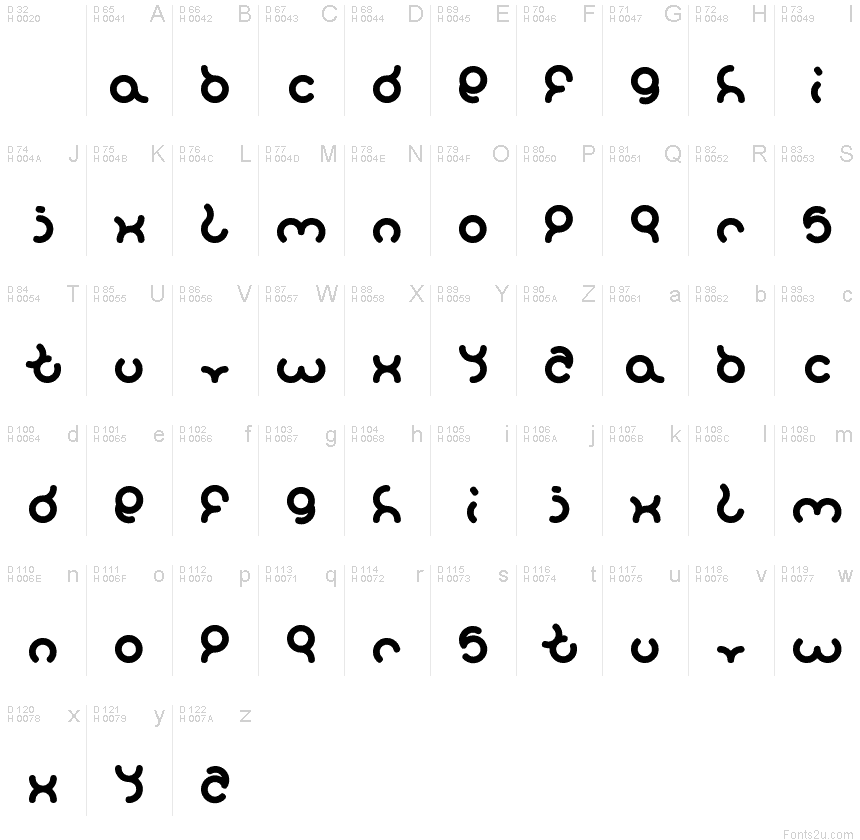
Dear Lady Sandra to darmowy, zabawny krój pisma w stylu retro, z miękkimi, zapętlonymi literami i radosnym klimatem lat 70. Zaokrąglone kształty wyglądają, jakby zostały naturalnie wylane na stronę, łącząc pełne, masywne brzuszki z delikatnie zakręconymi końcówkami, co nadaje krojowi swobodny, lekko groovowy rytm.
Naturalnie pasuje do nagłówków plakatów, grafik w stylu okładek albumów, opakowań butików, identyfikacji wizualnej kawiarni czy radosnych banerów w mediach społecznościowych, gdzie darmowy font potrafi samodzielnie nadać ton całemu projektowi. Dzięki temu, że litery są kompaktowe i krągłe, krój świetnie sprawdza się również w krótkich tytułach, napisach na okładkach czy monogramach, które wymagają ciepłej i nieszablonowej sylwetki.